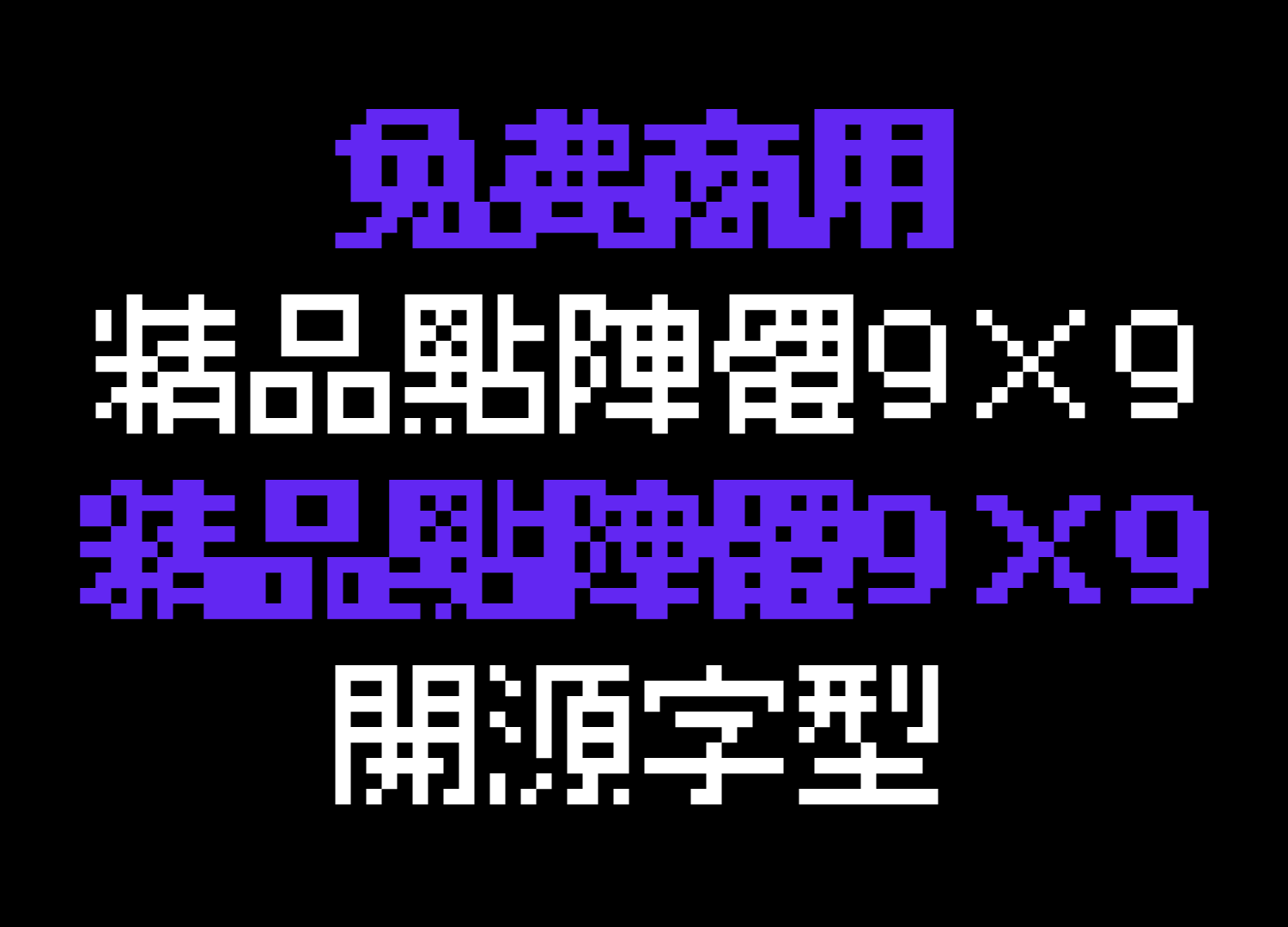
精品点阵体 9x9 Gradient
别称:BoutiqueBitmap9x9 Gradient / 精品點陣體 9×9 Gradient
概述
BoutiqueBitmap9x9/精品點陣體9×9/精品点阵体9×9
《精品點陣體9×9 (BoutiqueBitmap9x9) 》家族是一款基於M+ BITMAP FONTS及ベストテン(BestTen-DOT)改作的字型,并以缝合像素字体作作為字符補充,目的為適合在繁體中文環境中使用。我們改正了一些標點符號、日本習慣寫法、增加大量字符與Opentype特性——包括顏文字用符號、簡體中文、直排特性等——使字型使用更方便!
這是一款帶有極強烈的點陣風格的字型,非常適合用在像素畫、遊戲相關主題等等。